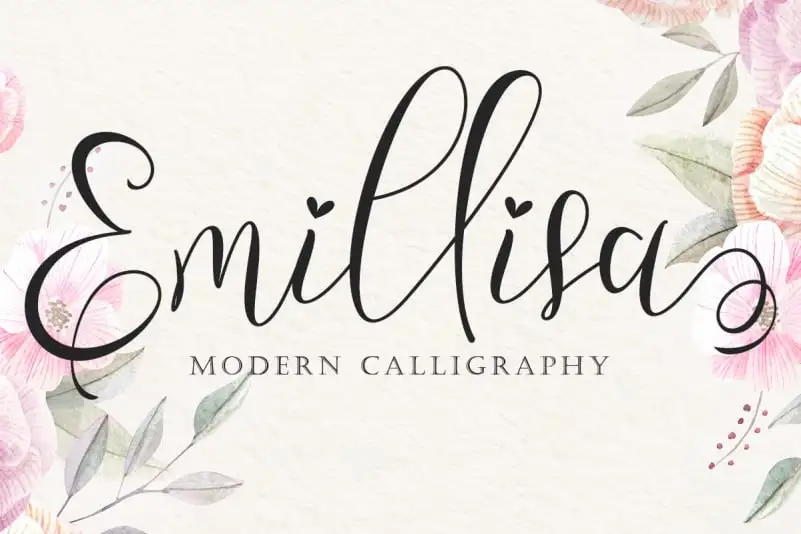
Emillisa Calligraphy Font – Download Grátis
Emillisa Calligraphy Font é uma fonte cuidadosamente criada a partir das mãos humanas, com uma delicadeza discreta que resulta num alto nível de qualidade. Esta fonte é extremamente bonita e elegante, sendo perfeita para qualquer tipo de trabalho. É especialmente adequada para necessidades relacionadas ao casamento (invites de casamento, fotografia de casamento, decorações e outras criações de eventos nupciais). Também é uma ótima escolha para promover negócios: desde hoteis até locações de férias em produtos ou serviços. É igualmente apropriada para atualizações de promoção, logotipos, marca, cartazes e postagens de status nas mídias sociais. Com o estilo moderno e sofisticado da Emillisa Calligraphy Font, você terá todas as ferramentas necessárias para expressar sua personalidade na web ou em qualquer projeto gráfico. Composta por Yoga Letter, essa fonte irá adicionar um toque de elegância sem deixar de ser funcional, tornando-a uma opção ideal tanto para os designers profissionais quanto para aqueles que desejam incorporar nuances de arte à sua própria identidade visual.